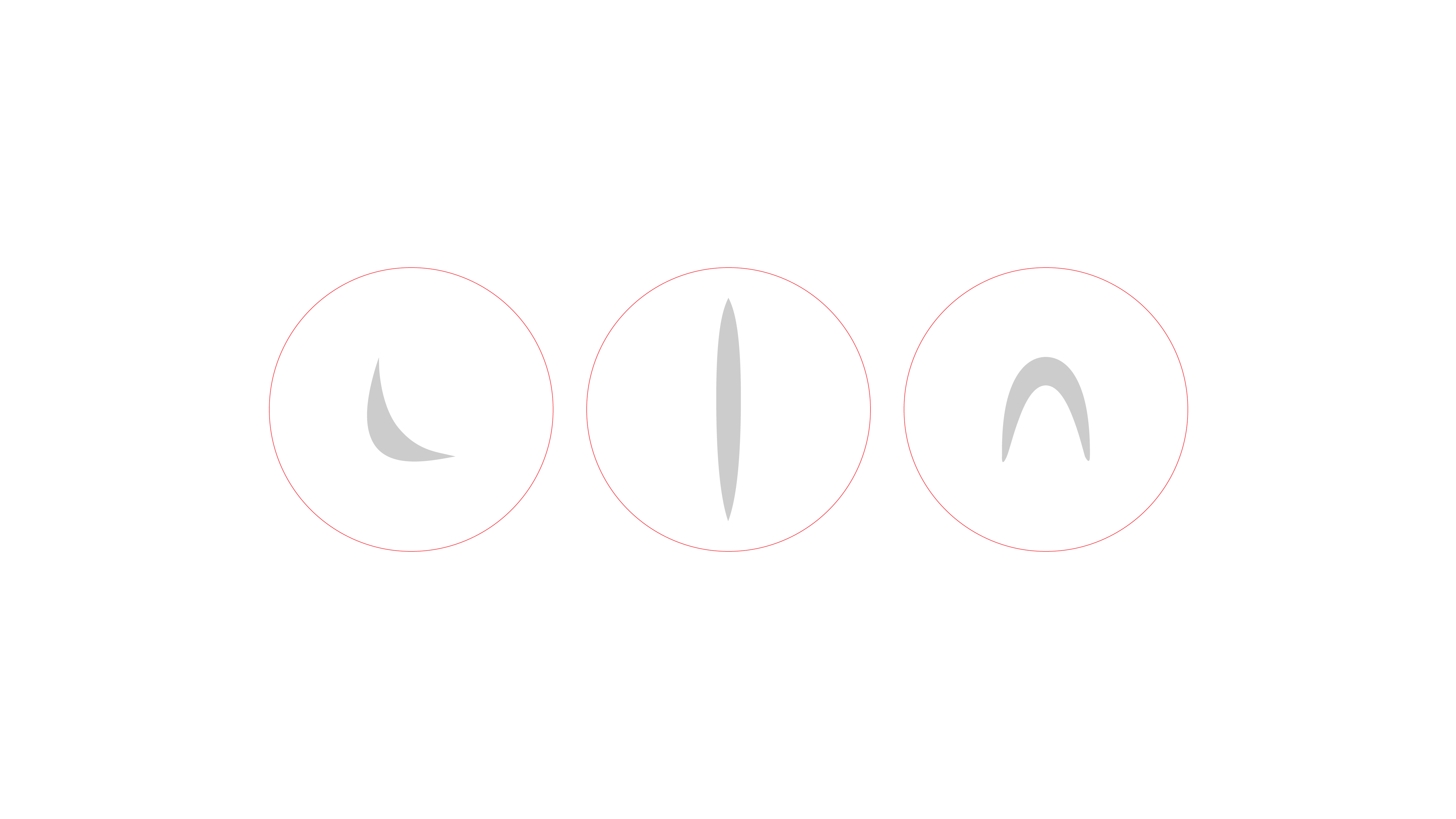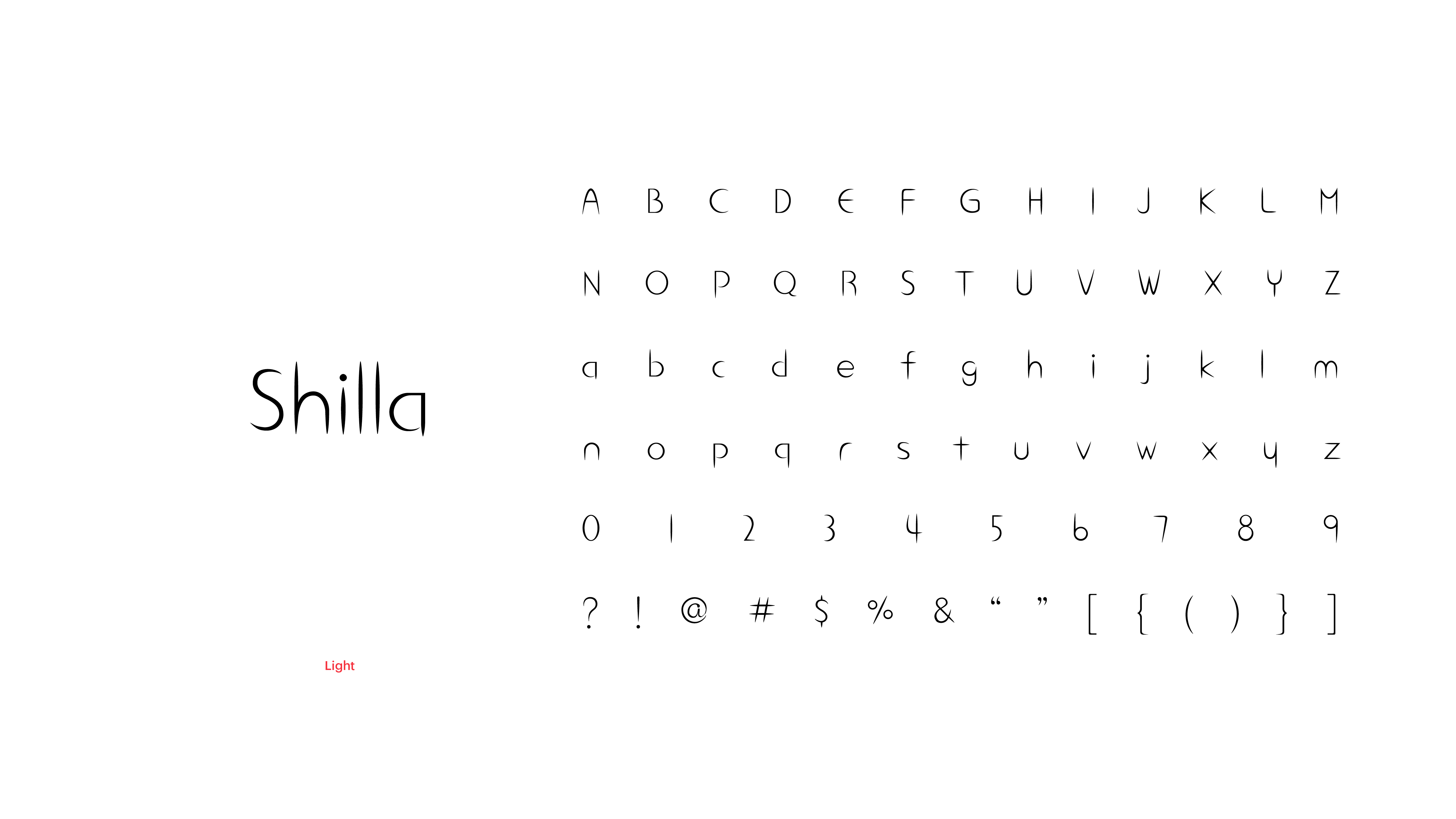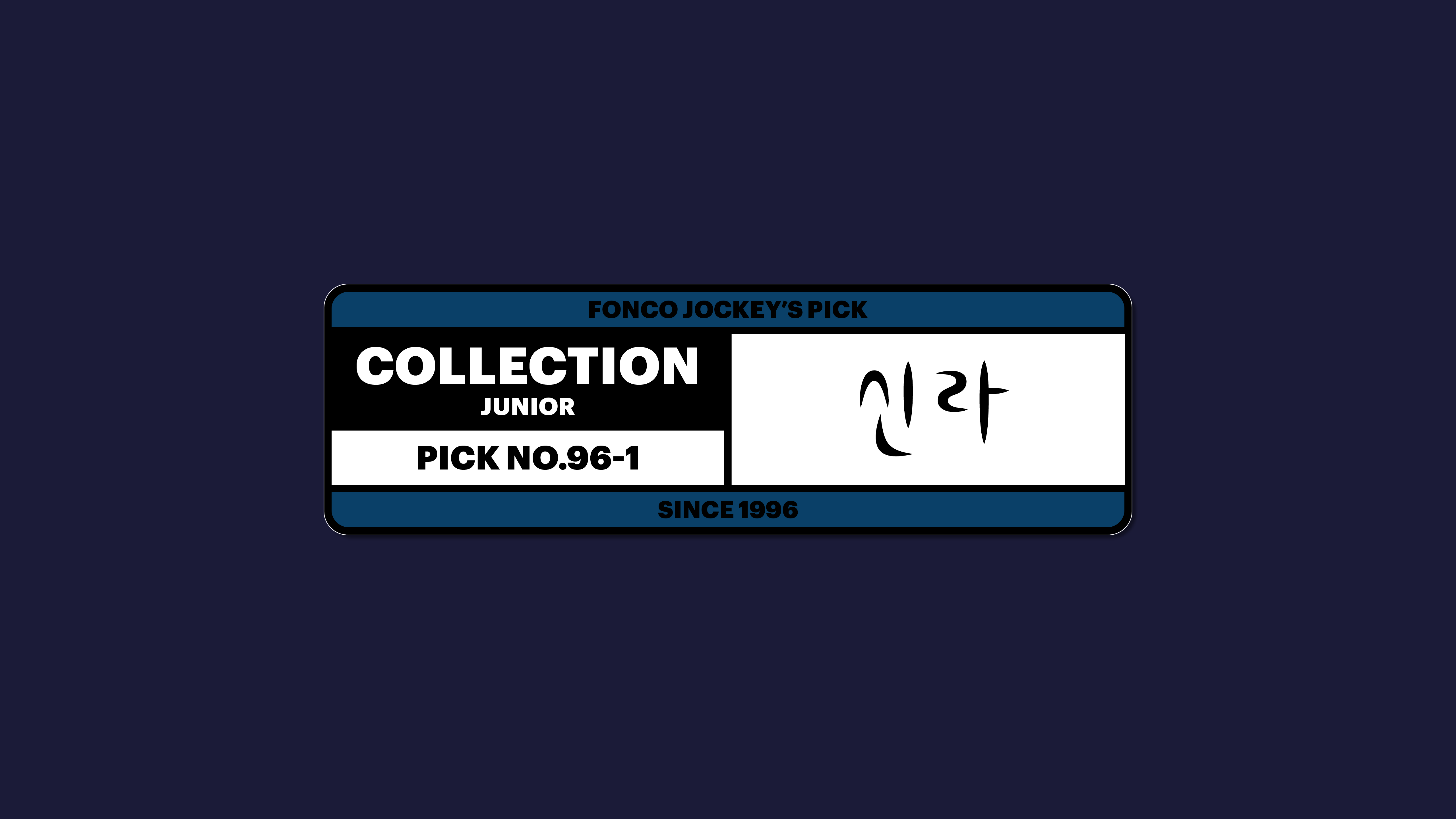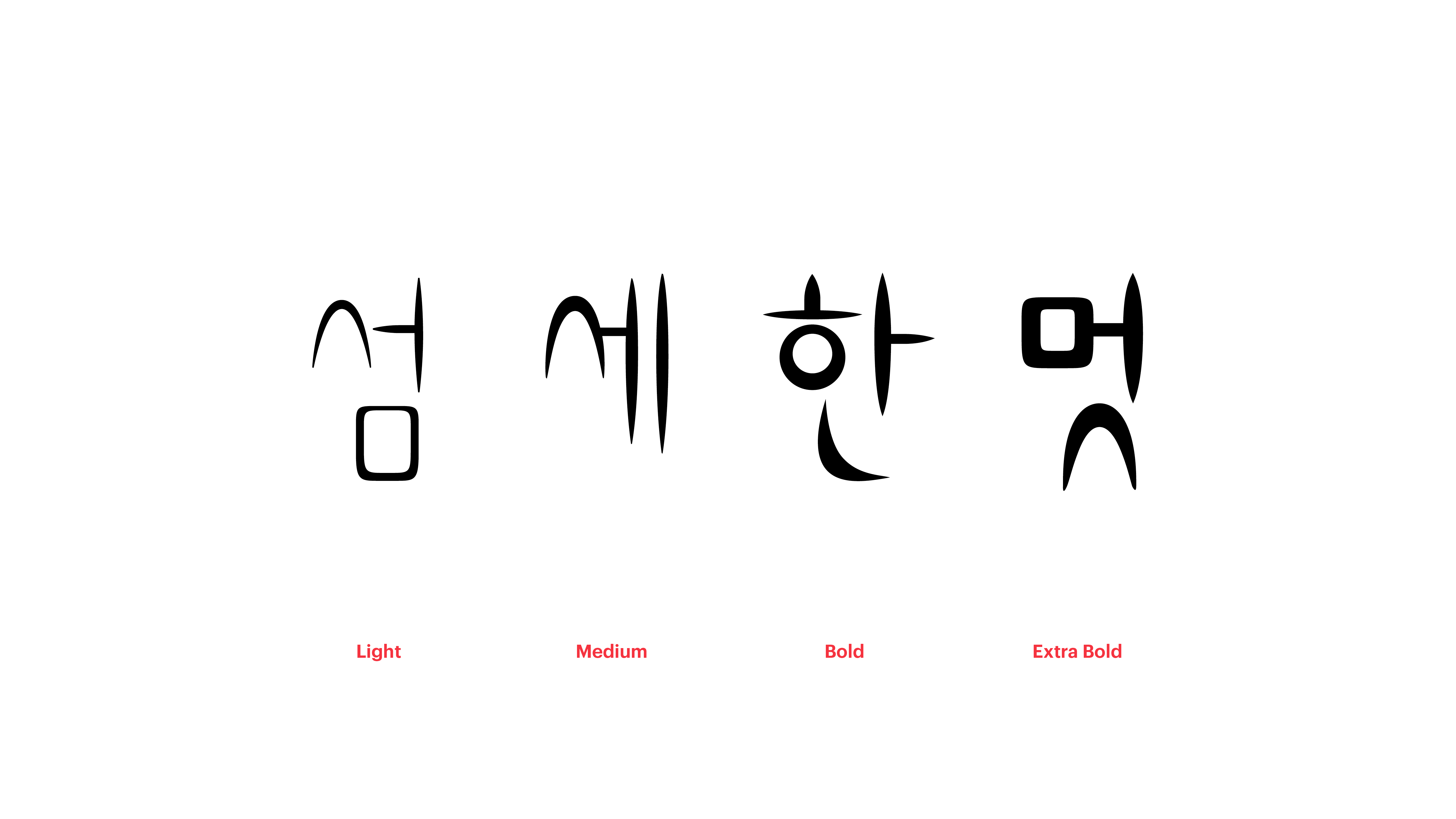
신라
Yoon 신라
화려하고 섬세한 빛으로 반짝이는 금관 문화를 품고 있는 신라. 그 유려하고 섬세한 멋을 그대로 담아낸 폰트입니다. 탈네모꼴이지만 윗줄을 가지런히 맞추어 자유로운 동시에 단정한 느낌을 살렸고, 흐르는 듯한 곡선 표현으로 섬세한 아름다움을 극대화해두었습니다.